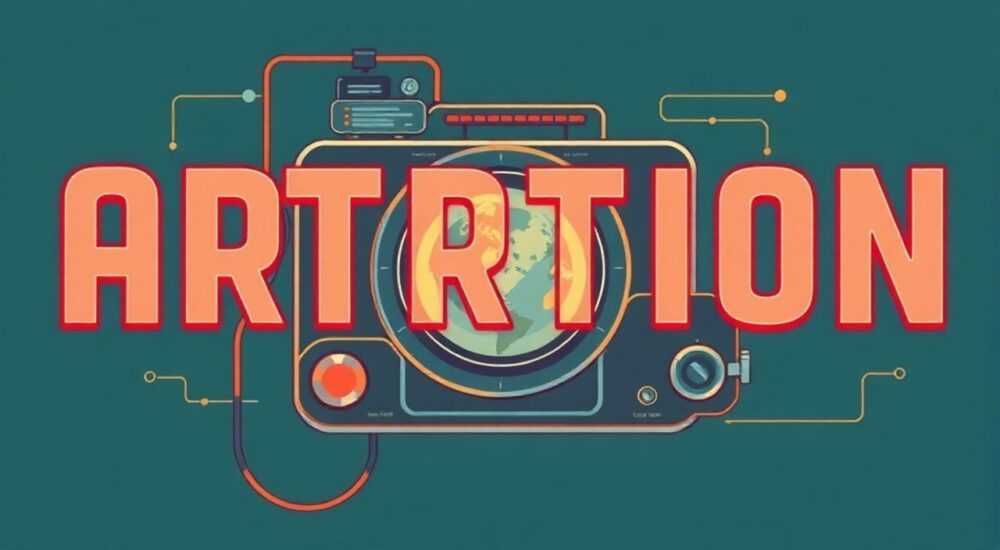
Шрифт в стиле футуризма
Шрифт в стиле футуризма представляет собой уникальное явление в мире типографики, сочетающее в себе художественные и технологические инновации начала XX века. Это направление возникло на волне стремительного развития промышленности и технического прогресса, когда художники искали новые способы выражения современности через визуальные средства. Особый интерес представляет то, как футуристические шрифты отражают динамику движения, скорость и энергию новой эпохи, создавая неповторимую эстетику, которая остается актуальной и сегодня.
Исторические корни футуристической типографики
Футуристический стиль в шрифтовом дизайне зародился в Италии в начале 1900-х годов, став неотъемлемой частью одноименного художественного движения. Философия футуризма, основанная Филиппо Маринетти в 1909 году, провозглашала отказ от прошлого и прославление современности. В этот период появилась необходимость в новых формах визуального выражения, которые могли бы передать революционный дух времени.
Особенностью футуристических шрифтов стало радикальное отступление от традиционных канонов типографики. Художники экспериментировали с формой букв, разрушали привычные пропорции и правила композиции. Появились динамические элементы – буквы словно двигались по плоскости, пересекались, накладывались друг на друга. Такое решение было призвано отразить хаотичность и многослойность современной жизни.
Характеристика |
Традиционный шрифт |
Футуристический шрифт |
Геометрия букв |
Строгая, симметричная |
Асимметричная, динамичная |
Расположение текста |
Линейное |
Многонаправленное |
Читаемость |
Варьируется |
Ключевые особенности футуристического шрифта
Среди основных характеристик футуристических шрифтов выделяют несколько важных аспектов. Прежде всего, это динамичность форм – буквы часто имеют острые углы, диагональные линии и асимметричные элементы. Такое решение создает ощущение движения даже в статичном изображении. Например, в работах Джино Северини буквы буквально «разлетаются» по плоскости, образуя сложные композиции.
Цветовая палитра футуристических шрифтов также отличается экспрессией. Художники активно использовали контрастные сочетания, металлические оттенки и неоновые эффекты, что символизировало индустриализацию и технологический прогресс. Интересно отметить, что многие приемы футуристической типографики позже легли в основу современного цифрового дизайна.
Другой важной особенностью стал отказ от стандартной горизонтальной строки. Текст мог располагаться под различными углами, пересекаться с другими элементами или формировать сложные пространственные конструкции. Это отражало футуристическое восприятие мира как постоянно меняющейся, многомерной реальности.
Практическое применение футуристических шрифтов
Сегодня шрифты в стиле футуризма находят широкое применение в различных областях дизайна. Особенно популярны они в рекламе технологических продуктов, где важно передать инновационность и прогрессивность бренда. Компании, работающие в сфере IT и цифровых технологий, часто используют футуристические шрифты для создания логотипов и фирменного стиля.
В киноиндустрии этот стиль незаменим при создании титров научно-фантастических фильмов и сериалов. Например, культовый дизайн титров сериала «Черное зеркало» демонстрирует современную интерпретацию футуристической типографики. В видеоиграх футуристические шрифты помогают создать атмосферу киберпанка или футуристического сеттинга.
- Разработка фирменного стиля технологических компаний
- Оформление научно-фантастического контента
- Создание рекламных материалов для инновационных продуктов
- Дизайн музыкальных обложек в электронных жанрах
- Оформление тематических мероприятий и выставок
Экспертное мнение: взгляд профессионала
Александр Кузнецов, арт-директор крупного дизайн-агентства «Future Design Studio», более 15 лет специализируется на создании футуристических шрифтов и типографических решений. По его словам, современные технологии значительно расширили возможности работы с футуристическими шрифтами:
«Когда я начинал свою карьеру, создание футуристического шрифта требовало огромных временных затрат и мастерства в традиционной графике. Сегодня же программы вроде Adobe Illustrator и специализированные шрифтовые редакторы позволяют экспериментировать практически без ограничений. Однако важно помнить о базовых принципах читаемости и функциональности.»
Александр отмечает, что наиболее успешные проекты всегда находятся на грани искусства и практичности. «Мы работали над проектом для крупной IT-компании, где нужно было создать шрифт, который одновременно выглядел бы футуристично и оставался удобным для чтения в пользовательском интерфейсе. Решением стала гибридная система, где базовые символы оставались узнаваемыми, но имели характерные футуристические акценты.»
Вопросы и ответы по теме футуристических шрифтов
- Как правильно использовать футуристические шрифты в веб-дизайне?
Важно соблюдать баланс между эстетикой и функциональностью. Рекомендуется использовать их для заголовков и акцентных элементов, оставляя основной текст в более традиционных шрифтах.